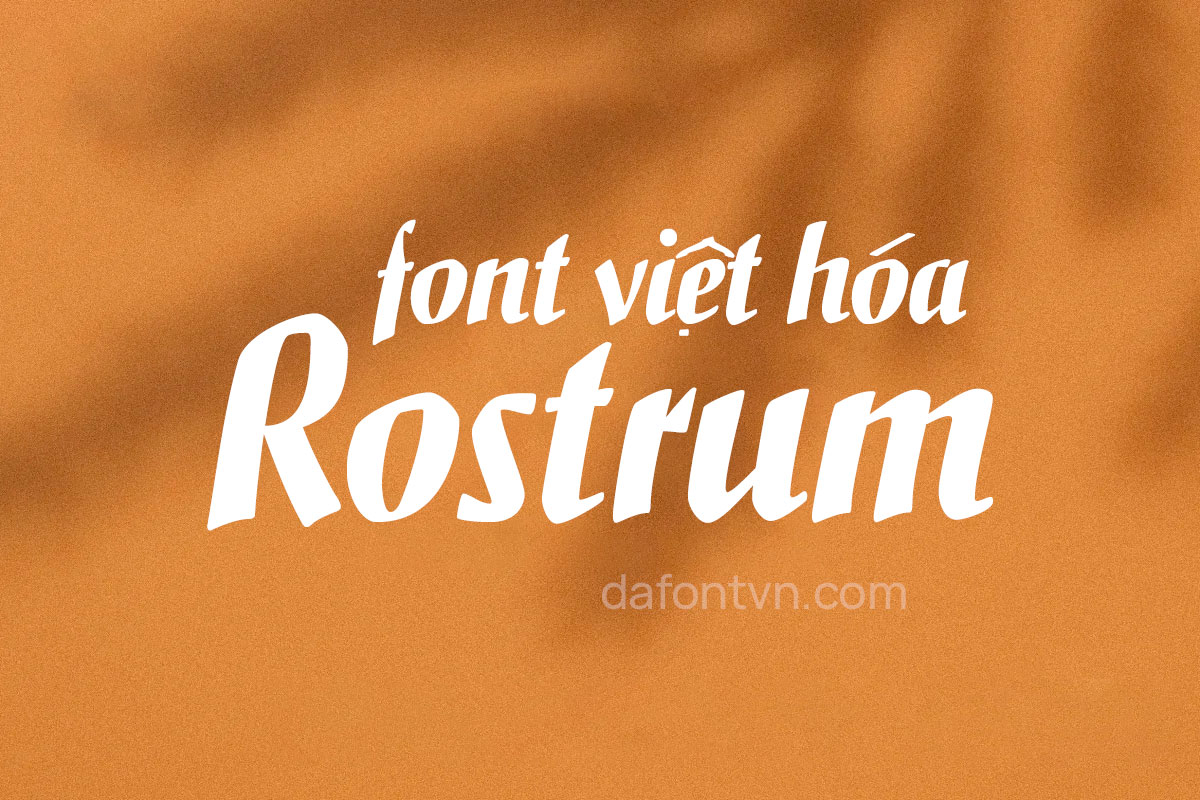
Font iCielBC Rostrum Việt Hóa, font được việt hóa bởi iCiel đây là một trong những font miễn phí nằm trong bộ font Hòn Ngọc Viễn Đông. Rostrum font được thiết kế bởi Julius Kirn dựa trên những thiết kế chữ cho xưởng đúc Genzsch và Heyse ở Hamburg năm 1938.